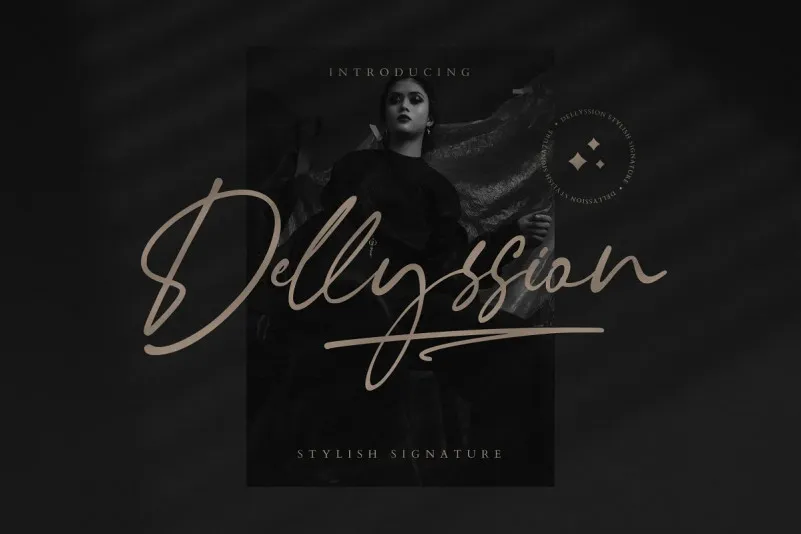
A fonte Dellyssion é uma elegante tipografia script que traz uma pitada romântica aos seus projetos digitais. Cuidadosamente criada para quem busca uma combinação perfeita de classe e romantismo, esta fonte está repleta de personalidade e delicadeza, tornando-a um recurso excepcional tanto para designers quanto para empresas. Suas linhas fluidas e sutis são ideais para aplicação em variados projetos gráficos, como logotipos, design de casamentos, posts nas redes sociais, publicidade, embalagens de produtos, desenho de produtos, rótulos, fotografia e até mesmo códigos de água-marinha. Com a Dellyssion Font, você encontra um toque autêntico e elegante para seus projetos que requerem uma pitada de letra à mão. Seja na criação de anúncios poderosos ou em designs pessoais únicos, sua natureza elegante e romântica a torna uma fonte irresistível para qualquer projeto onde um toque delicado seja necessário.